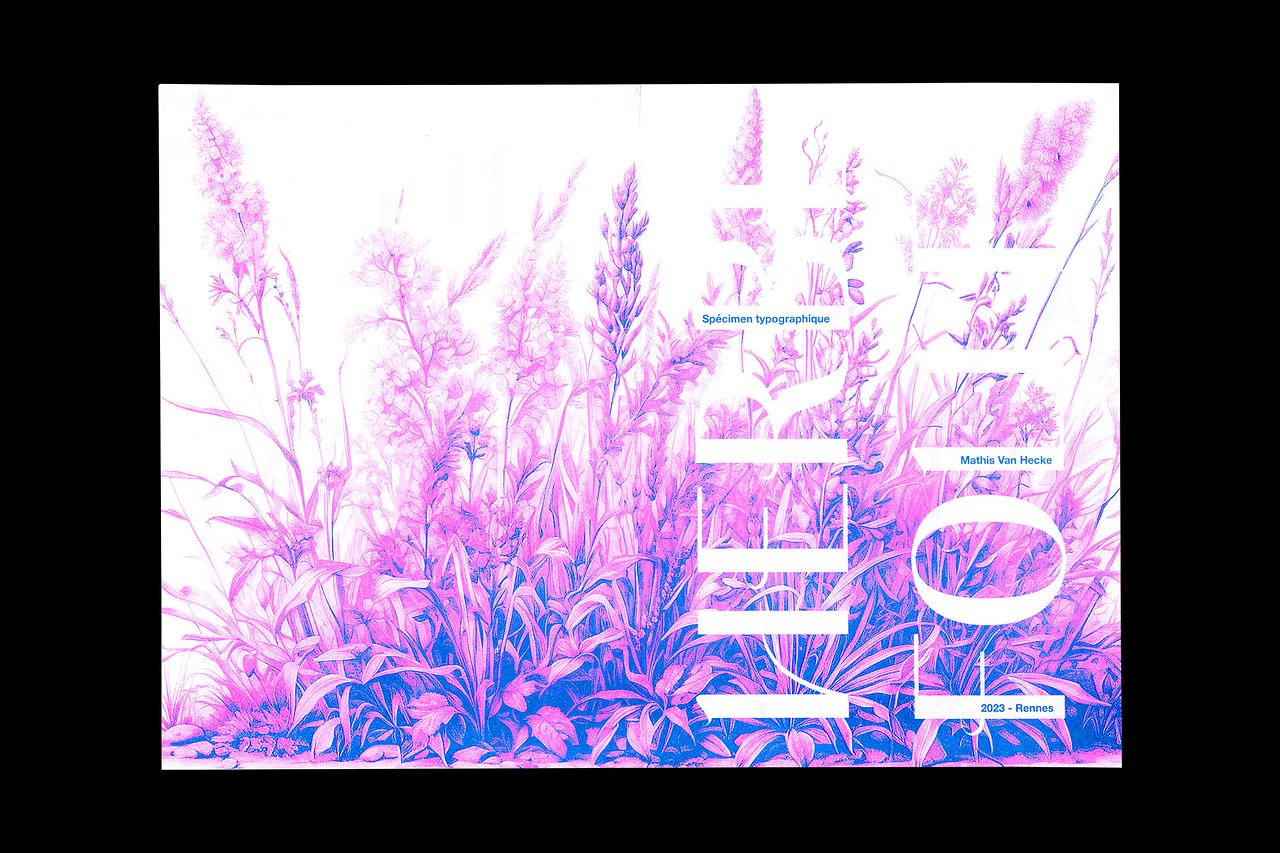
HERBE FOLLE — typeface
Typographie créée lors d'un workshop avec le typographe Thierry Fétiveau. Le style des caractères est contrasté et fin. Des courbes placées dans les lettres rappellent le végétal et la botanique. Cette police uniquement en capitales est destinée aux titres.